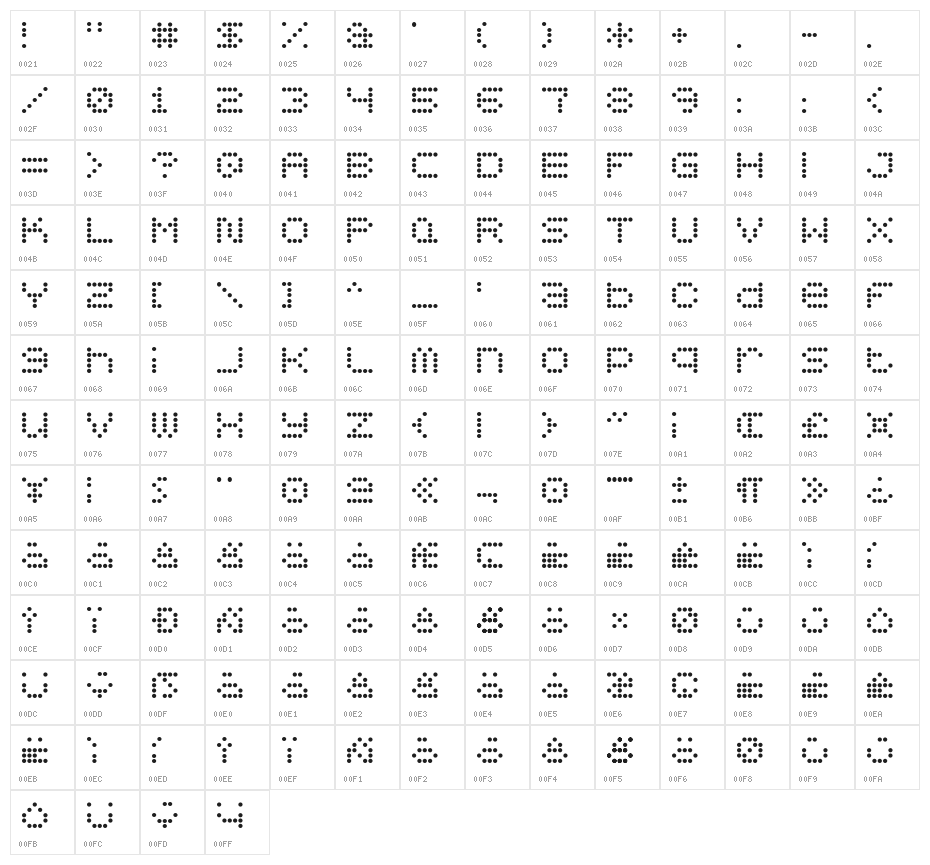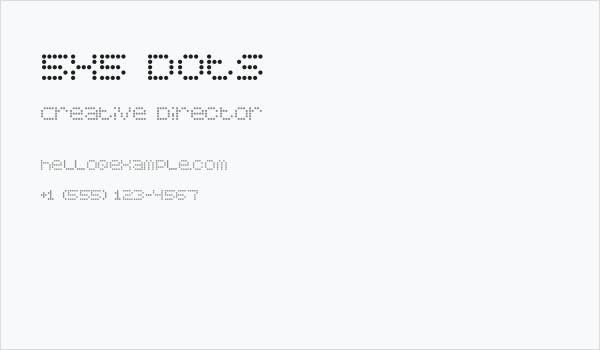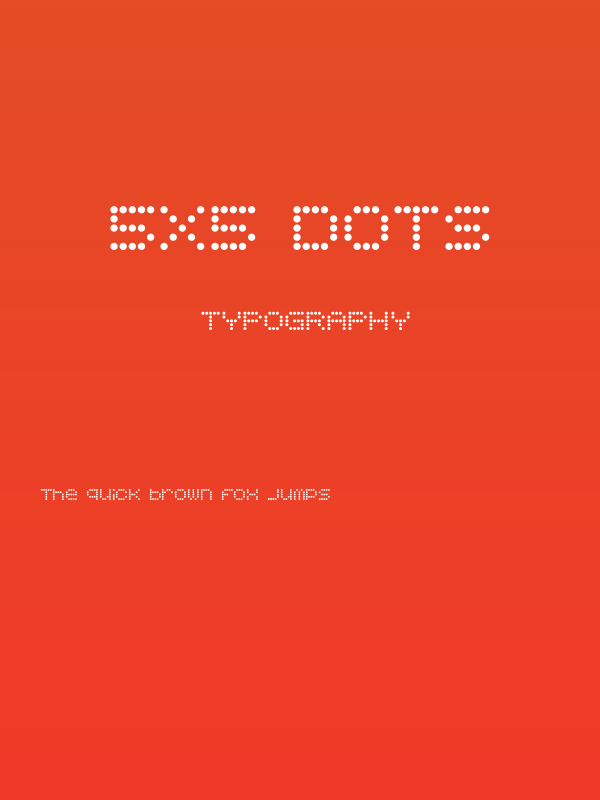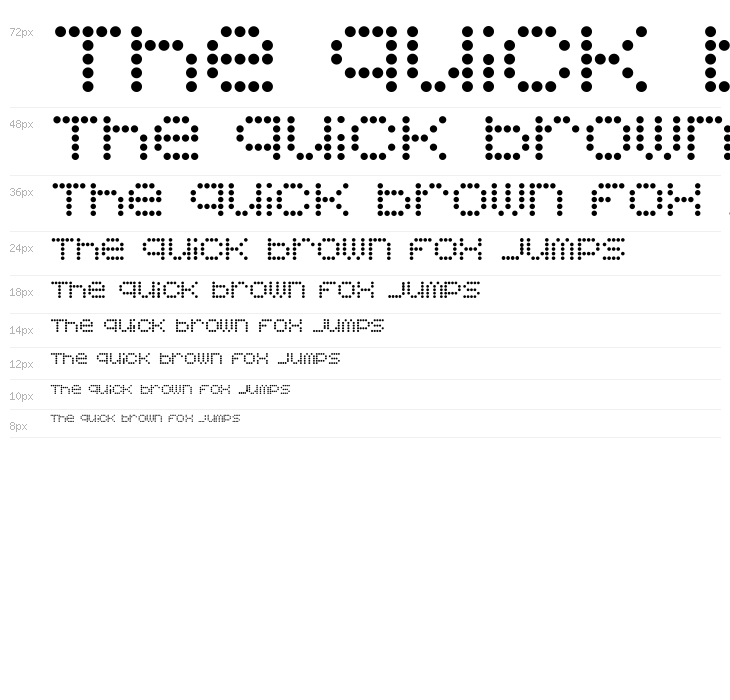
5x5 Dots Font
| Gesamtstil | Retro, Modern |
| Anwendungsfall | Logos, Digital displays, Creative projects |
| Vorgeschlagene Projekte | Ideal for digital displays, retro-themed designs, tech-related branding, and creative projects that require a unique and playful typeface. |